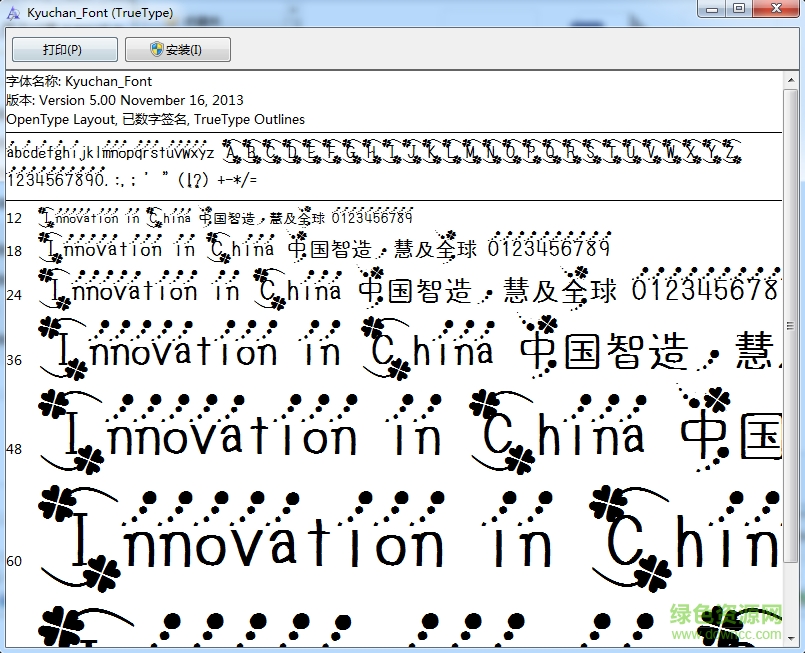
清醒著幸福是一款非常優(yōu)美可愛(ài)的幸福字體,四葉草和流星的造型點(diǎn)綴讓你的文本設(shè)計(jì)更顯藝術(shù)傳神,喜歡的朋友快來(lái)綠色資源網(wǎng)免費(fèi)下載吧!
清醒著的幸福字體很文藝,結(jié)構(gòu)上選用了四葉草和流星雨的圖案,給大家滿滿的幸福感。